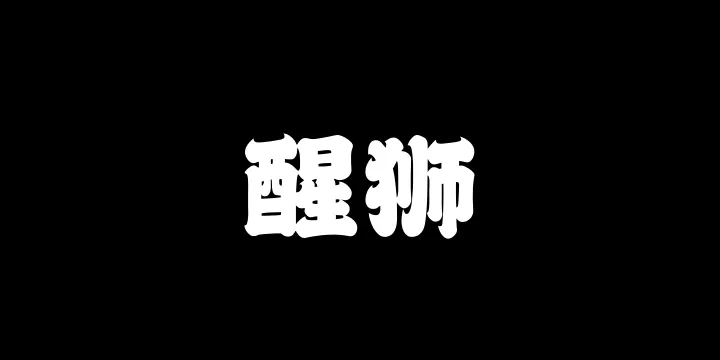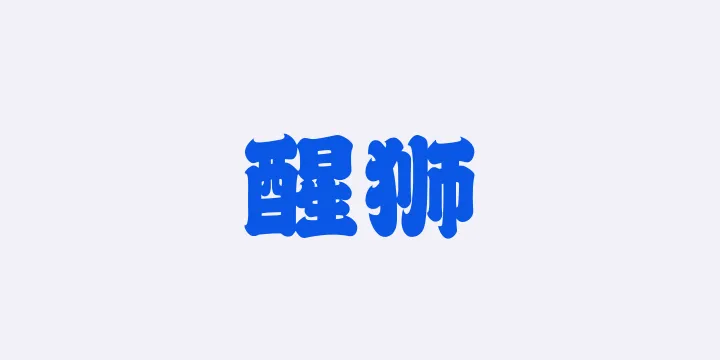
字体简介: 山海醒狮,是一款全新的字体,包含汉字9169个,符号200+个,是一款擘窠大字榜书字体。该字体雄健有力,非常醒目!融入楷书特点,有力、宽厚、方正,如同巍峨的大山,充满了稳重感和设计感。古朴浑厚,笔画与字形间透露着榜书的古雅和刚劲的特点,在浑厚的同时而又极富张力,桀骜不驯的特性,霸气外露。它的笔画充满力量感,组合搭配极富强烈的节奏感。在粗细的纵横间,拥有非常规的张力特性。